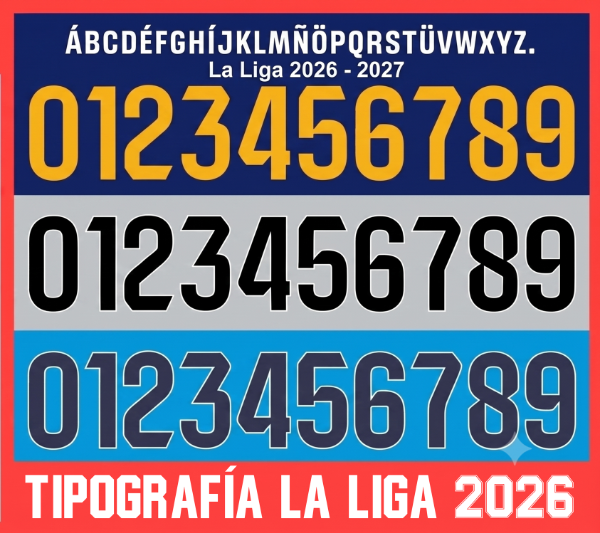
Tipografía Números Fuente Camisetas LA LIGA ESPAÑOLA 2026
Tipografía oficial de LaLiga española de fútbol para la temporada 2026-2027, utilizada en los nombres y números de los jugadores de todos los equipos participantes tanto en la Primera como en la Segunda División.